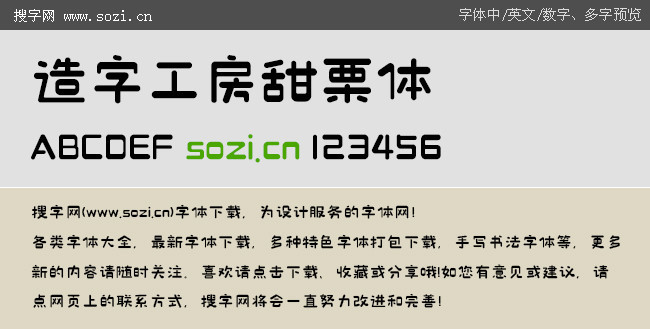
造字工房甜栗體
搜字網(wǎng)給大家提供一款造字工房甜栗體中文字體下載,造字工房甜栗體字形扁潤(rùn)、圓渾醇厚,線條與結(jié)構(gòu)的和諧統(tǒng)一令其嚴(yán)謹(jǐn)而不刻板、凝重而有韻致,字存隸意,結(jié)構(gòu)圓備平穩(wěn)勻整,縱橫郁拔,天真樸拙。適用于大標(biāo)題、包裝設(shè)計(jì)、海報(bào)設(shè)計(jì)等應(yīng)用。(本字體為個(gè)人非商用版,如需要商用請(qǐng)聯(lián)系官方購(gòu)買版權(quán))